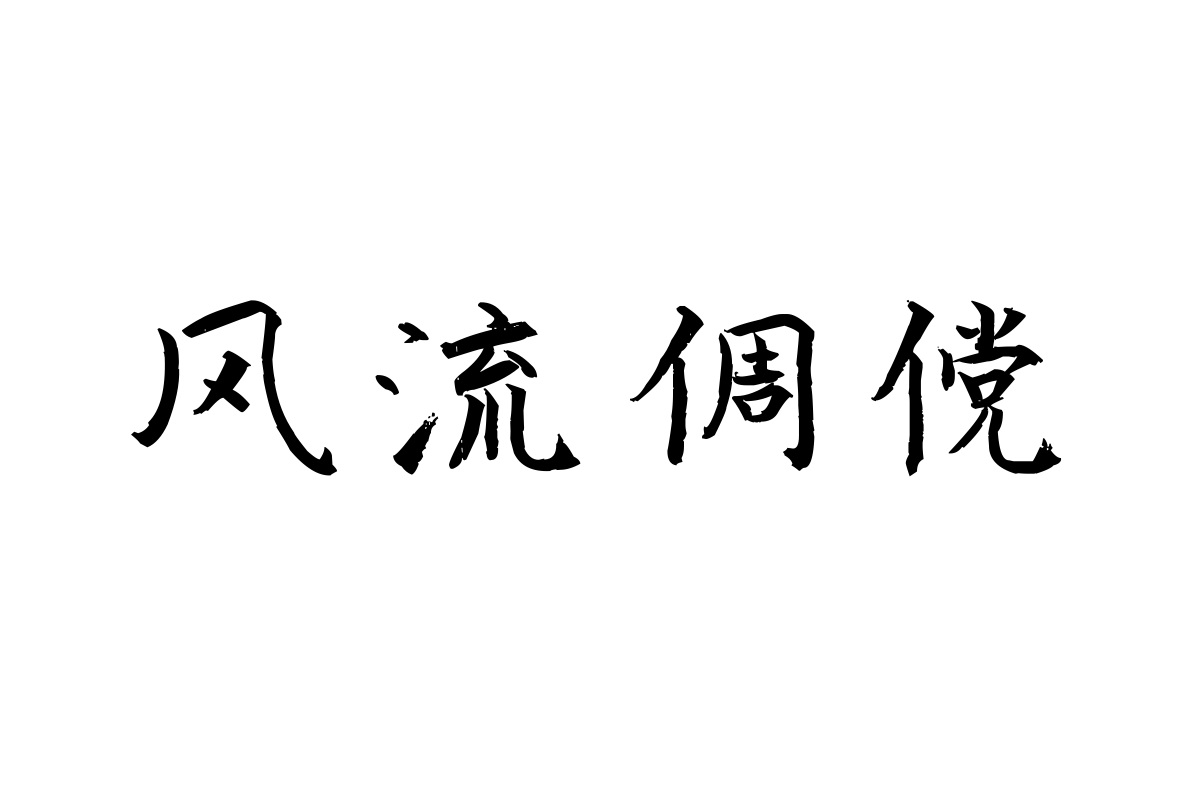
蝉羽喜山堂楷书是一套以汉字书写为特色的字体,它由书法家陈云龙创作。这套字体的特点是笔势流畅,结构严谨,线条清晰,给人以古朴典雅的感觉。它的笔画粗细变化丰富,既有刚劲有力的线条,又有柔和细腻的笔触,展现出汉字的美感和韵味。此外,蝉羽喜山堂楷书还注重字与字之间的空间布局,使得整个字体看起来更加和谐统一。总的来说,蝉羽喜山堂楷书是一种具有独特魅力和艺术价值的书法字体。